電車の車内広告、本の表紙、商品のパッケージ、美術館のサイン、などなど挙げたらきりがないですがタイププロジェクトのフォントは至る所で見かけます。スタッフブログでも使用事例紹介の記事がありますが、見かけたときに社内で報告しあっています。
入社して間もない頃は、通勤中や出かけたとき目に入ってくる文字を見つつタイププロジェクトのフォントを意識的に探すようにしていました。最初は見分けるのに自信がなく、見かけたら写真に撮って後で照らし合わせたりしていました。
私の場合の覚えやすかった形を挙げてみます。仮名で言えばAXIS Font、TPスカイ、TP明朝は「あ、お、き、ら」。タイププロジェクト以外のフォントでもそうですが、同制作者の別書体を見ると、書いた人の線の気持ちよさや癖がこの筆の動きなのかな、特徴づける形になっているのかなとぼんやり想像してます。
漢字で言えばTPスカイのハイとミドルのハネと、点や右ハライなどの末広がりの形のすっきり具合。TP明朝は角ウロコと、ローとミドルの点の収筆の丸み具合。それに加えて各フォントの細部の形やコントラストのつき方です。
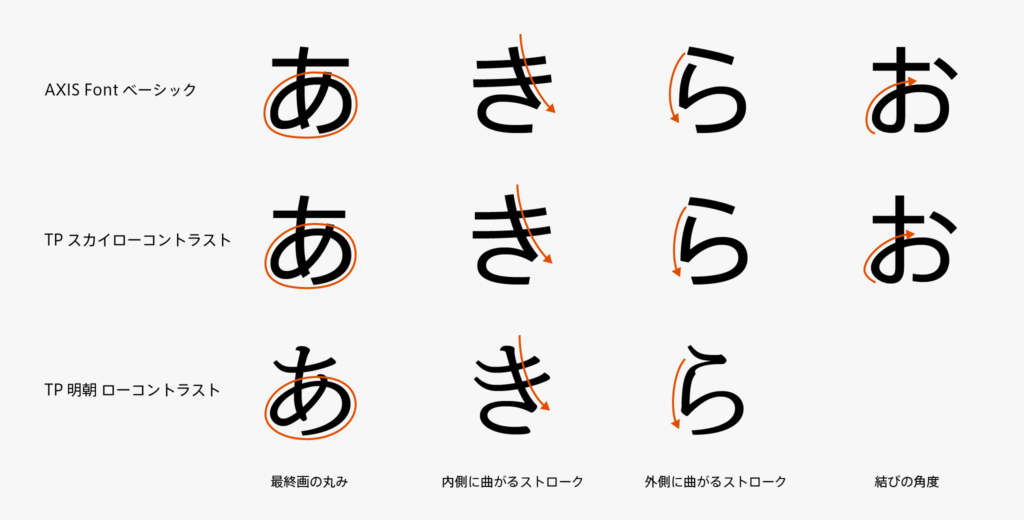
そうしているうちに自社フォントの形とまとう雰囲気のようなものがわかるようになりました。
上記挙げてみて人それぞれ違っていそうなので、他の人が見分けている場所はどこなのだろうと気になりました。